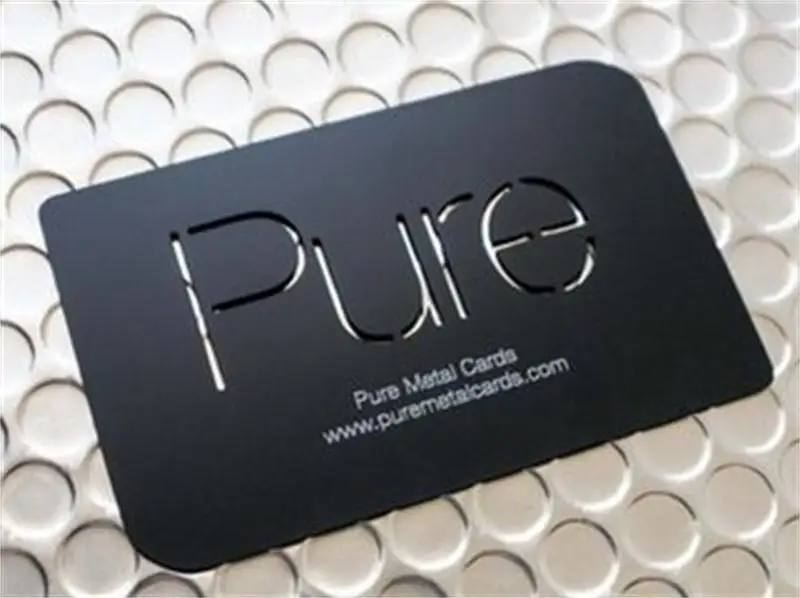
Выбираем лучший шрифт для визитной карточки
Какой наилучший шрифт для визитной карточки? Точного ответа на этот вопрос не существует. Известно лишь то, что шрифт «помогает» визитной карточке правильно выполнять свою «работу»: запоминаться. В интернете есть множество сайтов с платными и бесплатными гарнитурами и выбор огромен, поэтому легко запутаться. Попробуем предложить интересные варианты
Общие замечания
Размер визитной карточки очень мал. При этом она должна вмещать всю необходимую контактную информацию, иметь привлекательный внешний вид и вызывать положительные эмоции. Ведь зачастую именно с нее начинается знакомство с новыми заказчиками и партнерами. Иллюстраций на этом печатном изделии практически нет: в основном, все сводится к логотипу. Поэтому шрифт — это и основной текст, и основной декор (в комплексе с качественной печатью и после печатной отделкой). Вот почему так важно подобрать интересную, но в то же время читабельную гарнитуру.
Eurocine
Крупный шрифт, который отлично подходит для заголовков, логотипов и брендинга.
В семействе представлены различные варианты начертания, поэтому подобрать что-то подходящее несложно. Вдохновением для создания этой гарнитуры послужили постеры к европейским фильмам 1970-х. Шрифт одновременно гламурный и резкий, привлекает толстыми линиями и стимулирует желание повторно взглянуть на печатное изделие.
Milkshake
Приятная и нескучная гарнитура отлично подходит для визиток и личных резюме. Толстые и солидные буквы для многих становятся излюбленным выбором. Он выглядит дружественно, читабельно и при этом очень универсален. Создается впечатление рукописного текста чернильной ручкой.
Sofia Pro
Веселый и гармоничный шрифт для различного применения, представленный во многих языках. Придает некую игривость, одновременно с чувством баланса. Может использоваться как доминантная гарнитура для заголовков или для обычного текста мелким кеглем.
Quicksand
Прекрасный выбор для изящных визитных карточек. Аккуратные линии выглядят привлекательно и напоминают моду 1920-1930-х.
Geometria
Различные геометрические варианты шрифтов без засечек практически не выходят из моды уже около столетия. Geometria сочетает в себе динамические элементы и определенную стабильность. Шрифт подходит для длительного чтения, при этом прекрасно выглядит и может использоваться для запоминающихся заголовков. В зависимости от контекста, он будет и игривым, и серьезным. Может восприниматься как винтажный, так и передовой. Также это отличное решение для минималистичного дизайна.
Neuton
Neuton — отличный выбор для тех, кто предпочитает шрифты с засечками. Он немного напоминает привычный многим Times. Отличается компактной шириной, благодаря чему позволяет сэкономить место и хорошо смотрится на экране. Хорошо впишется в классический или современный дизайн визитки, также подходит для личных документов. Довольно популярен среди молодежи.
Alcubierre
Alcubierre — прекрасная гарнитура для легкого и воздушного дизайна. Чистые линии, мягкие формы — своеобразный глоток свежего воздуха.
Визитки с таким шрифтом, непременно, произведут приятное впечатление.
Aileron
Aileron делает визитку более «серьезной» и прекрасно смотрится на странице, благодаря округлым и мягким формам. Может применяться не только для визиток, но и для всей корпоративной продукции, так как очень универсален.
Ubuntu
Шрифт часто используют технологические компании, программисты и инженеры. Это относительно «молодая» гарнитура, разработанная в 2010 году вместе с одной из версий программного обеспечения Ubuntu.
Ambarella
Гарнитура превращает визитку в изделие ручной работы, изготовленное каллиграфом. Придает неповторимый шарм печатному продукту. Особенно изысканно будет смотреться на матовой бумаге в комплексе с тиснением фольгой.
Shadows Into Light
Еще один вариант гарнитуры, напоминающей рукописный текст. Игривый и веселый, очень молодежный. Может хорошо подойти музыкантам.
Futuracha
Очень вычурный шрифт, красивый и таинственный. Но лучше использовать его для лого, нежели для большого отрезка текста.
Часто его выбирают дизайнеры, художники и модельеры.
Итак, шрифт в визитных карточках играет важную роль, определяя общий стиль визитки. Используйте оригинальные нетрадиционные гарнитуры, привлекательные и запоминающиеся. Однако не стоит пренебрегать и читабельностью, ведь основная функция визитки — доносить информацию.
Дизайн визиток — cекреты успеха — Студія ІДЕЯ Бровари
В современном мире бизнеса не обойтись без визитных карточек. В них содержится в лаконичной форме вся контактная информация о фирме или частном лице. Визитка – ваша идентификация в обществе. Визитными карточками обмениваются на деловых встречах, беседах, при знакомстве с будущими компаньонами и клиентами, при прощании; их раздают на выставках и презентациях.
Студия ИДЕЯ обязательно предложит вам различные варианты визиток. Личные визитки используются непосредственно тем лицом, контактные данные которого указываются на визитной карточке.
Elixia
Слова почти не поддаются простой красоте этого шрифта. Изящная, как теория кристаллического поля, но изогнутая, как бриллиант огранки «императрица», Эликсия говорит сама за себя. И это может продолжаться сутками.
Шрифт Kust или Brux
Технически это два отдельных шрифта для визитных карточек, но они слишком круты, чтобы их упускать, так что сегодня вы получаете халяву.